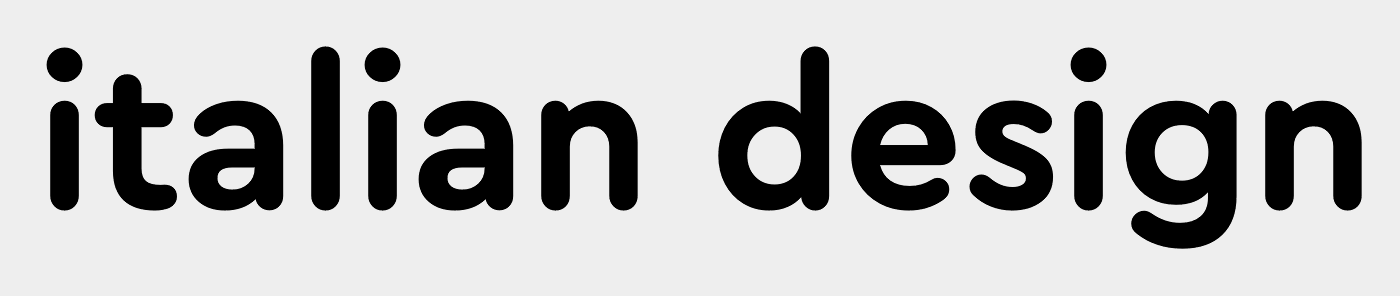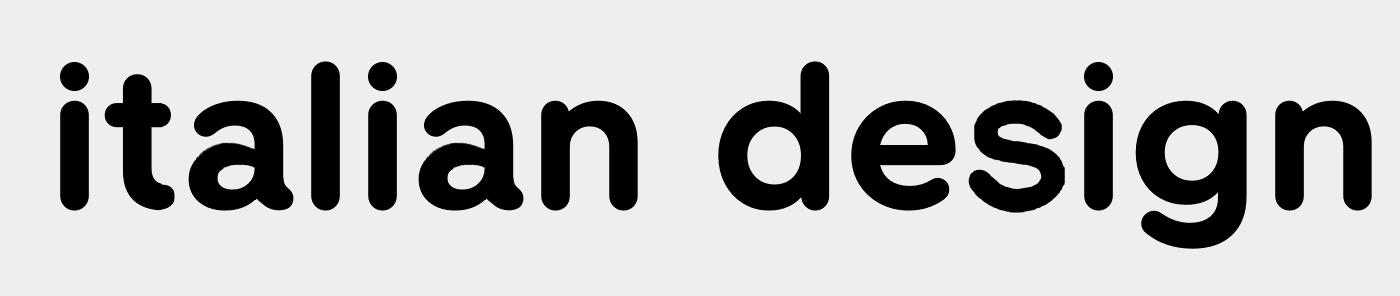
Schrift eines Designer-Logos auf einer Espressomaschine
Hallo ich suche die Schriftart eines Logos, welches auf einer Espressomaschine aufgedruckt ist, die ich restaurieren möchte.
Das Logo ist schon stark beschädigt und da es per Siebdruck aufgetragen wurde, schon von sich aus sehr verschwommen.
Es geht um die Schriftart des Textes "italian design".
Im Internet habe ich noch ein anderes Objekt des gleichen Designers gefunden, welches das Logo eingeprägt hatte. Ich habe den Text daraus extrahiert und als Bild angefügt.
Für eine automatische Erkennung war das Bild zu schlecht. Kann mir jemand sagen, um welche Schriftart es sich handeln könnte?
Wenn du uns mehr Hinweise gibst, wird es für alle leichter. Welcher Hersteller? Welches Baujahr(zehnt)? Welcher Designer?
Hersteller: Gaggia Milano
Baujahr: um die 1975, es wurden andere Maschinen mit diesem Logo aber auch schon in den späten 60ern gebaut.
Designer: Giuseppe de Götzen
Aus den 1960ern … dann war das höchstwahrscheinlich keine heute als Font erhältliche Satzschrift.
"xpert2000" aus dem Kaffenetz hat ebenfalls eine orange LL, vielleicht ist der Schriftzug bei ihm besser erhalten, dann könnte zumindest eine sehr ähnliche Schriftart gefunden werden.
an Logos habe ich inzwischen 3 von verschiedenen Maschinen zusammengetragen. Gerade der Schriftzug "italian design" ist aber bei allen dreien schlecht. Noch dazu kommt, dass der Aufdruck damals wohl per Schablone erfolgte, was dazu führte, dass die Buchstaben leicht verlaufen sind und dazu noch bei jedem Aufdruck anders. Damit kam ich also nicht weiter.
Deshalb habe ich den geprägten Schriftzug von einem Bialetti-Kännchen extrahiert, dort sind die Buchstaben klarer zu erkennen.
Ich habe mir auch schon diverse Schriftarten angeschaut aber alle Merkmale konnte ich nirgends zusammenbringen.
Sollte diese Schriftart nicht mehr zu finden sein, würde ich alternativ auch eine möglichst ähnliche verwenden. Da ich das Logo wohl auch wieder per Siebdruck aufbringen werde, würden sich leichte Unterschiede auch dort wieder verwischen.
Also falls jemand eine Idee für eine weitgehend ähnliche Schriftart hat, würde ich mich sehr freuen.
Ich fang mal mit einer zumindest ähnlichen an:
Vielen Dank für die Vorschläge! Ich wusste leider nicht, nach welchen Schlagwörtern ich in den Schriften suchen muss, um bestimmte Merkmale zu finden.
Ich habe mal eine Synthese aus allen drei Vorschlägen gemacht. Da ich nur diesen einen Schriftzug nachbilden muss und den auch nur für eine Siebdruckvorlage, benötige ich keinen kompletten Font.
Basis war der erste Vorschlag, der auslaufende Strich beim "a" (da gibts bestimmt einen Fachbegriff für) ist aus dem Zweiten und das "s" aus dem Dritten.  Ich denke so sollte es dem Original genügen. Vielen Dank! :-)
Tampondruck kannte ich noch nicht. Das Logo  ist ca. 5cm x 2cm groß. Was für Kosten kommen da auf einen zu?
Es ist ja nur eine einmalige Sache. Eventuell möchte noch ein weiter Nutzer mit einer ähnlichen Maschine dieses Logo nutzen aber auch dann sind es eben nur zwei oder drei Druckvorgänge.
Meine Tampondruck-Zeit liegt jetzt leider einige Jahre zurück, damals bedruckten wir damit Staubschutz-Masken aus speziellem Vlies.  Da brauchten wir auch Klischees für kleine Versuchs-Serien, und setzten hier diese UV-Belichtbaren Polymerplatten ein, und wir hatten dafür dann wirklich sehr wenig dafür bezahlt. Für die große Serie (einige 10000 Drucke) brauchte es dann aber Stahlklischees, die aber auch bezahlbar waren.
Suche dir vielleicht in der Nähe jemanden, der Werbegeschenke bedruckt.
Die Tampons für undere Maken hatten wir uns damals übrigens aus Silikon-Abformharz selbst gegossen. :-)
Ach so, ich vergaß zu erwähnen: Als Positv-Film reicht in diesem Fall ein Ausdruck eines Laserdruckers auf Overhead-Folie.